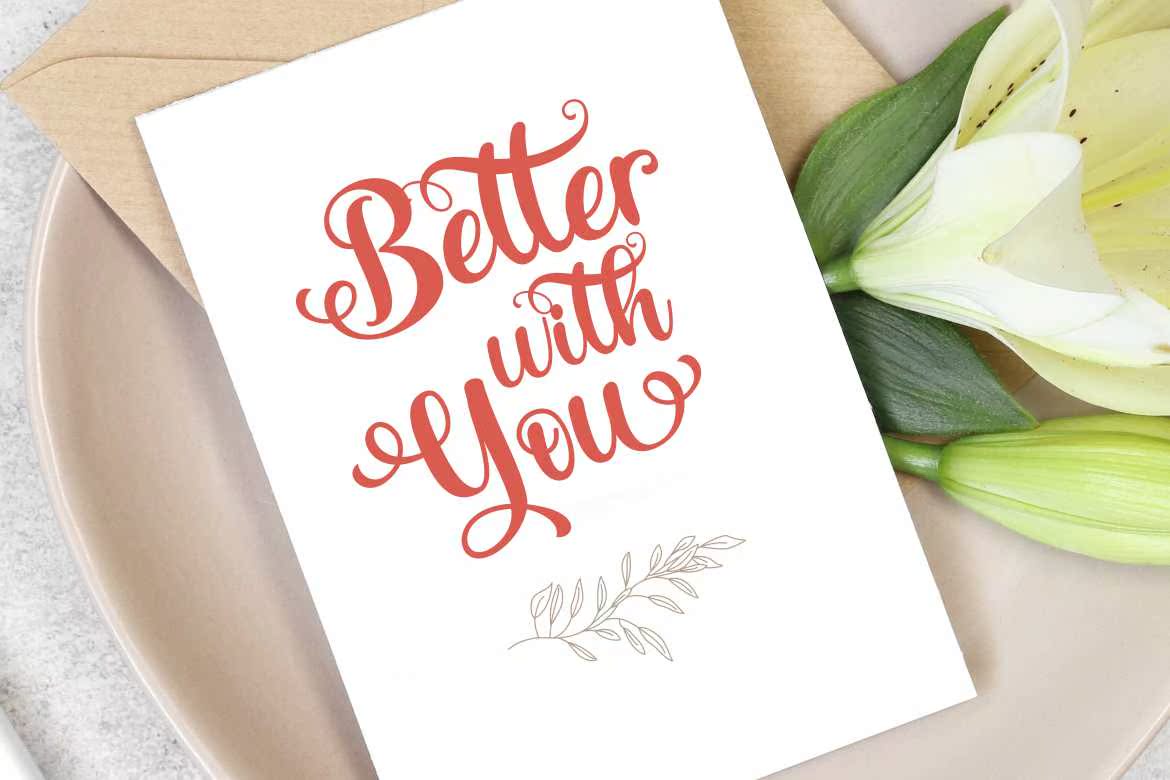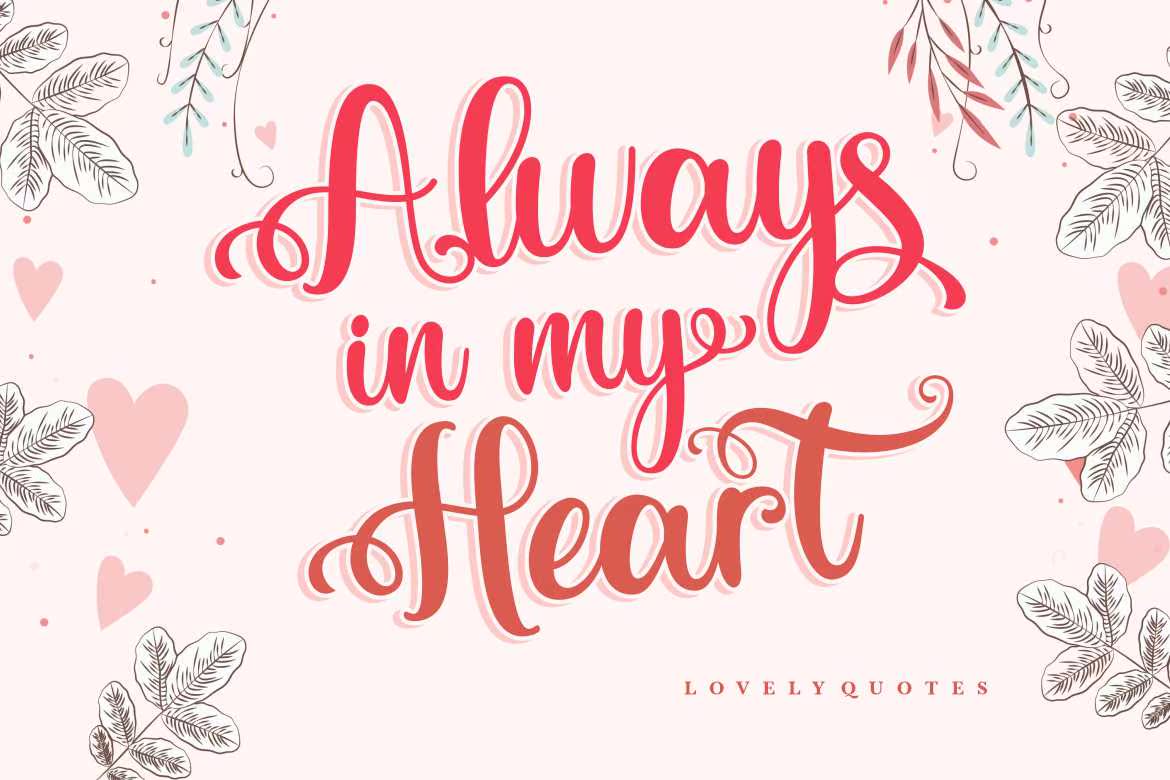
Valentina是一款现代女性手工书写字体,精心制作,深受用户喜爱。它的偶然性使它看起来非常贴近地球,易读,最终用途广泛。无论是在繁忙的背景下还是在独立的大标题下,Valentina都将在任何一个上下文中都能脱颖而出!Valentina是一款现代女性手工书写字体,精心制作,深受用户喜爱。它的偶然性使它看起来非常贴近地球,易读,最终用途广泛。无论是在繁忙的背景下还是在独立的大标题下,Valentina都将在任何一个上下文中都能脱颖而出!